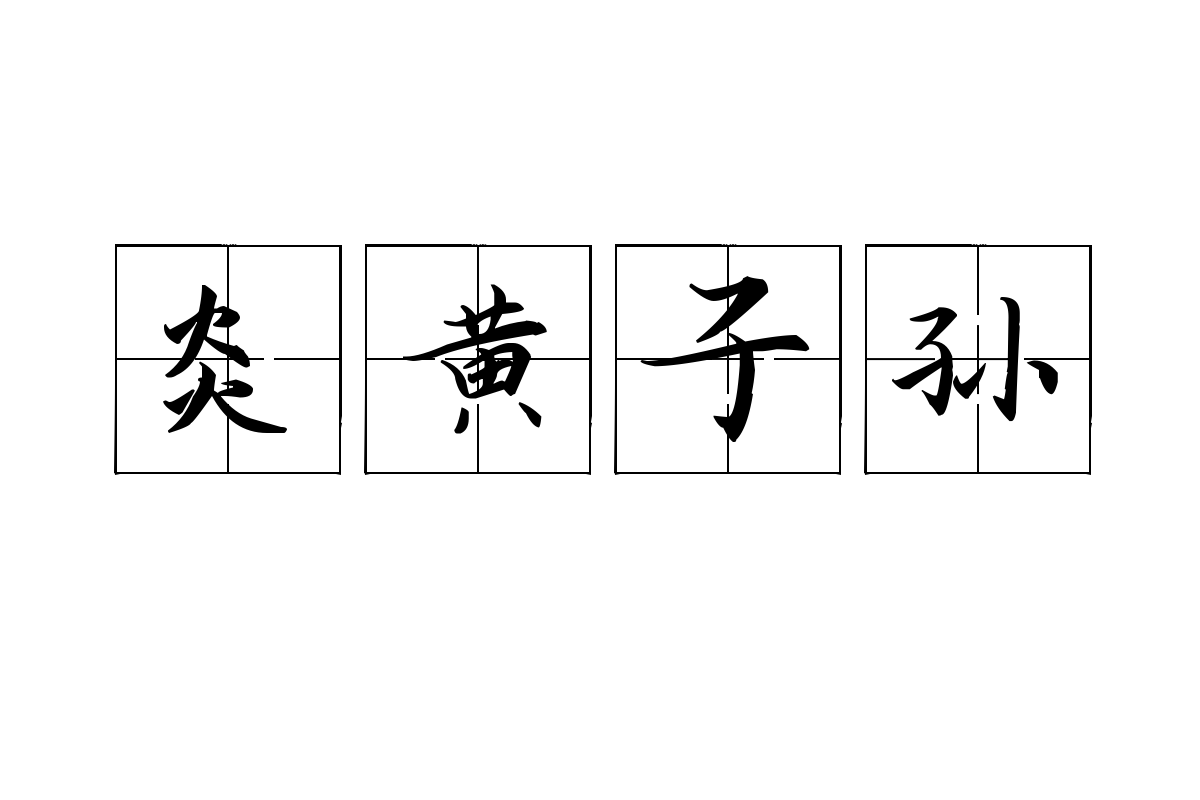
汉呈复古风字体,是一款具有浓厚中国古典韵味的字体。它汲取了古代汉字的形态特征,融合了现代审美理念,创造出一种既古朴又时尚的视觉效果。
该字体线条流畅,结构严谨,既有楷书的规整,又有隶书的古朴。其笔画粗细适中,既有力度感,又不失柔和感。整体风格典雅大方,适合用于各类文字设计,如标题、正文、广告等。
此外,汉呈复古风字体还具有很高的可读性。它的字形清晰易辨,笔画分明,无论是在印刷还是电子显示中都能保持良好的视觉效果。同时,该字体也具有一定的艺术性,能够吸引人们的注意力,提升作品的艺术品味。
总的来说,汉呈复古风字体是一款非常适合用于中文文字设计的优秀字体。无论是用于书籍、杂志、海报等出版物,还是用于网页、广告等新媒体平台,都能展现出独特的魅力和效果。